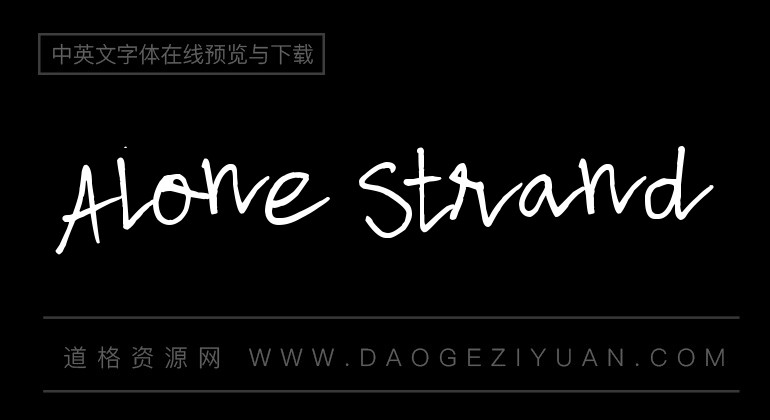
Alone Strand 是一款英文字体,由英国设计师Tommy Lee Wallace设计,由Fonts.com推出。这款字体具有细节丰富、精致优雅的特点,适合用于文字排版、标题、海报等多种场景。它具有独特的笔画,灵活的结构,可以为文字排版带来更多的创意,让文字更加有趣。内容介绍
Alone Strand是一款非常不错的手写艺术字体,具有很好的视觉感,适合于文化类的宣传设计、商业类品牌的广告和产品包装设计以及个性化文字排版等较多场景。